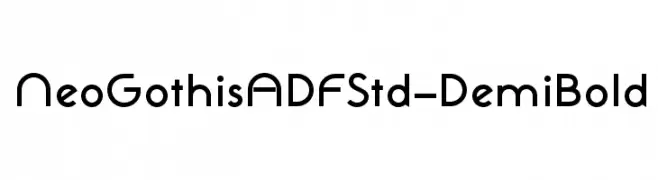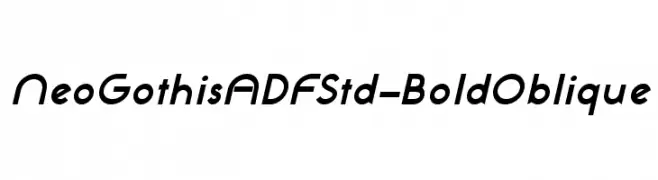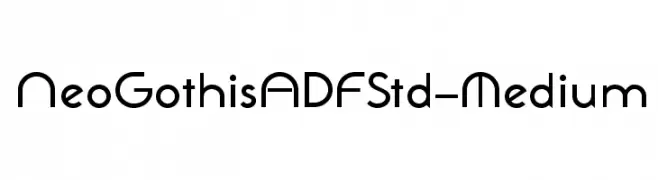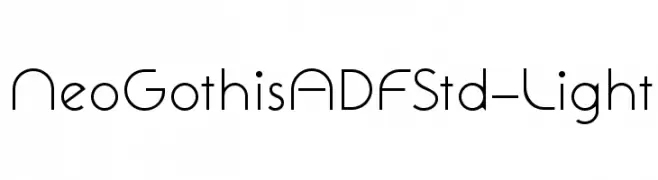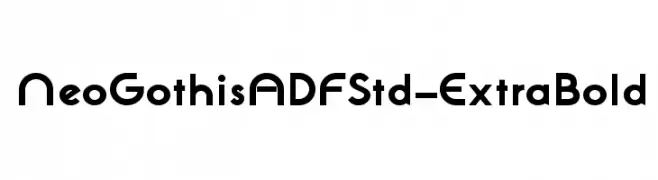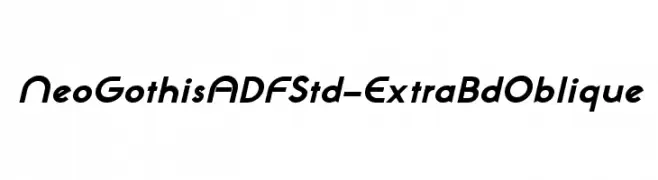
A modern, geometric font with clean lines and consistent stroke width.
A bold, modern font with geometric influences and clean lines.
A bold, modern font with clean, geometric lines and uniform stroke width.
A modern, bold, and slightly oblique font with geometric uppercase and rounded lowercase letters.
A bold, oblique font with modern, dynamic letterforms.
A modern, geometric font with a clean and sleek design.
A sleek, modern font with clean lines and a minimalist aesthetic.
A sleek, modern oblique font with dynamic curves and sharp edges.
A bold, geometric font with a modern and clean design.
A bold, oblique font with a modern and dynamic style.
近期热门包括 NeoGothisADFStd-Regular, NeoGothisADFStd-Bold, NeoGothisADFStd-DemiBdOblique and NeoGothisADFStd-BoldOblique 它们在清晰度与个性之间取得平衡,适用于科技品牌、编辑排版与社媒视觉。